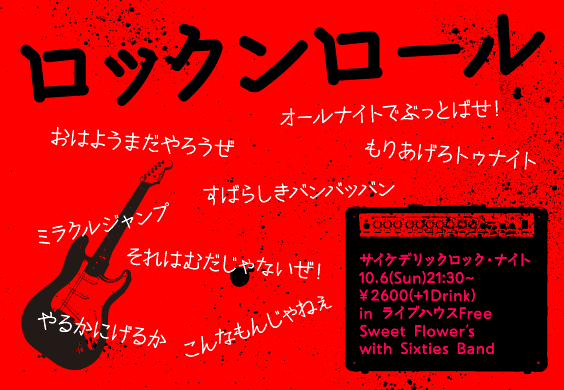
手書き風日本語フォント
kiyoshiro(きよしろう)フォントとは
きよしろうは手書き文字を参考にして作成した書体です。手書きの勢いを感じさせつつ統一感のある使いやすいフォント。文字のデザインにとんがった三角形の要素を多く取り入れた個性的な書体です。ひらがな、カタカナ、アルファベット、記号のみの書体ですが、一般的な丸ゴシックの漢字と組み合わせて使える、最適な線の太さになっています。
例えば、男性の強い意志を表す時、元気のある表現などに威力を発揮するフォントです。
ただの丸ゴシック体では物足りない、アクセントになる文字が欲しい時など用途は様々。太いボールドは見出しやタイトルにもピッタリです。手書きフォントよりも視認性が高く読みやすい、きよしろうフォントをぜひお試し下さい。この下に使用例サンプルを作ってみました。          |
Kiyoshiro(きよしろう)フォントを使った作例見本